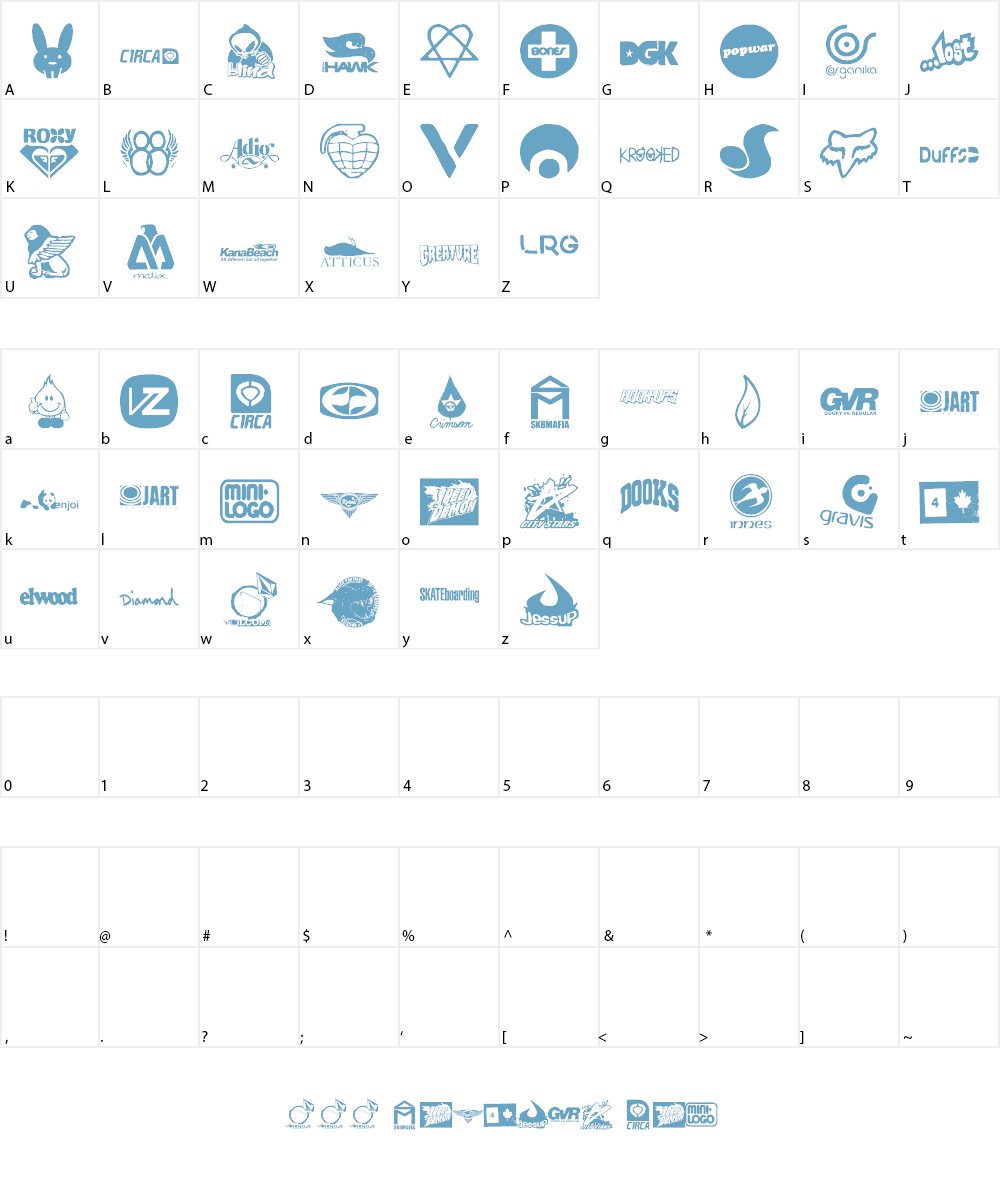
LOGOS Y MAS LOGOS DE SKATE!
me an mandado imeils que decian que faltaban logos, bueno ahora los que faltaban estan aca en mayuscula como en minuscula,